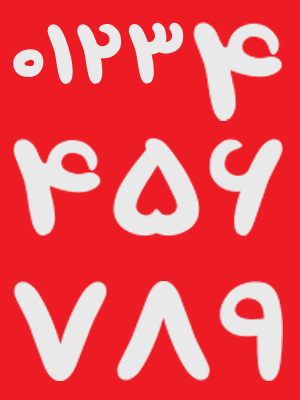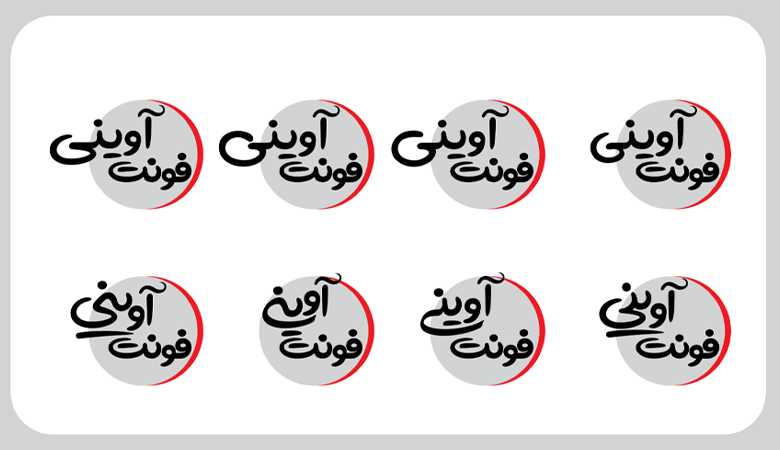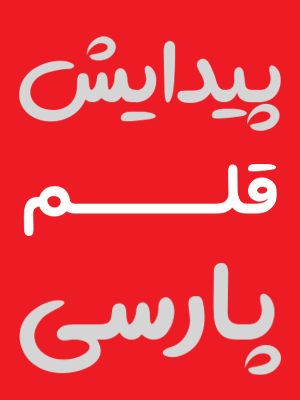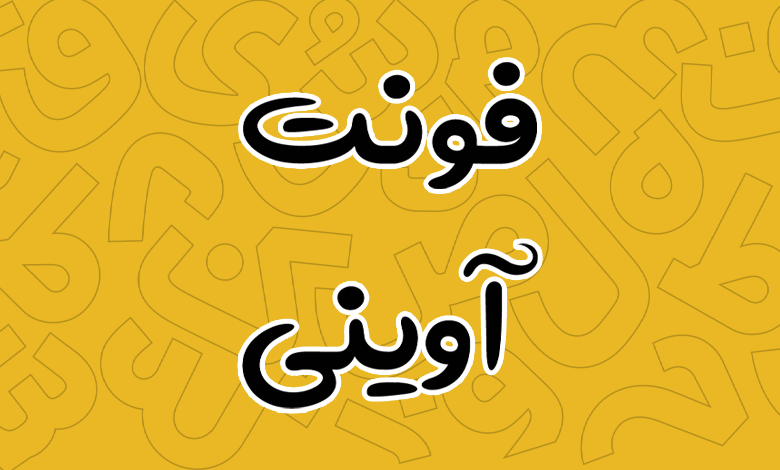
فونت آوینی (Aviny)
فونت آوینی (به انگلیسی: Aviny) فونت دستنویس فانتزی با ظاهری بسیار روان، پر تحرک و شاد است که در تمامی حروف از شکستگیها، دندانهها و قوسهایی بسیار نرم استفاده شده است. کاربردهای این قلم شامل فونت عناوین، نمایشی یا فونت مناسب تبلیغات و استفاده در متون کوتاه است. فونت آوینی رایگان نیست و در یک بسته با وزن معمولی رایگان جهت خرید ارائه شده است.
طراحی فونت آوینی بهدست قاسم نجاری صورت گرفته که دارای یک سبک خاص در ساخت فونتهای دست نویس و فانتزی است که پیش از این فونت جوان را از این طراح مورد بررسی قرار دادهایم. قلم آوینی نیز دارای یک حس جوان است که شادابی و نشاط را در متون شما ایجاد خواهد کرد.
در ادامه این نوشته از سایت فونتچی به نقد و بررسی کامل فونت آوینی خواهیم پرداخت که میتوانید با این فونتی که صرفا دارای یک وزن بوده اما امکانات و قابلیتهای متعددی در اختیارتان قرار خواهد داد آشنا شوید.
معرفی و بررسی فونت آوینی (Aviny)
فونت aviny در گروه فونت مناسب عنوان، دست نویس و مناسب تبلیغات گروهبندی شده است که برای استفاده در متون کوتاه، شعارهای تبلیغاتی و بهطور کلی هر جایی که نیاز به یک فونت دست نویس که ساختار کلی متون ما را تغییر داده و موجب جلب توجه شود کاربرد دارد.
سبک و وزن فونت آوینی
ساختار و شکل دست نویسی که این فونت میدهد میتواند برای ایجاد ارتباط صمیمیتر مورد استفاده قرار گیرد که توصیه میشود فقط در متنهای کوتاه از آن استفاده کنید.
از فونت اوینی میتوان در محیطهای مختلف دیجیتال و فضای آفلاین استفاده کرد. ساخت انواع عکس نوشته، طراحی بنرها و اسلایدرها برای سایتها و فروشگاهها، طراحی جلد کتاب در حوزه کودک و نوجوان، برنامههای تلویزیونی، ساخت کتابهای مصور و استفاده از این فونت در تیترها و عناوین هر چیز دیگری بیشترین کاربردهای این فونت هستند.
پشتیبانی از زبان عربی و انگلیسی
فونت آوینی فارسی جدایی از این زبان از زبانهای عربی و انگلیسی نیز پشتیبانی میکند. پشتیبانی از زبان عربی در این فونت مختص حروف و ترکیباتی که در زبان فارسی یکسان هستند نبوده و شامل اعراب و برخی کاراکترهای دیگر نیز میشود که همه گلیفها در هر دو زبان عربی و فارسی تا جای ممکن در حد استانداردهای بین المللی کار شده است.
شاید تنها ایرادی که بتوان در این خصوص به فونت آوینی گرفت، عدم اختصاص گلیفهای اعداد «۴۵۶» برای این زبان باشد که به شکل متفاوتی نسبت به زبان فارسی نوشته میشوند. انتظار هم میرود که با ارتقا این فونت به نسخه بالاتر این مورد برطرف گردد.
در خصوص زبان انگلیسی هم میتوان گفت که آوینی از فونت دیگری وام گرفته نشده و طراحی تمامی حروف لاتین بر اساس همان سبک دستنویس و فانتزی که برای زبان فارسی صورت گرفته، در زبان انگلیسی نیز پیاده سازی شده است.
دارای حروف و ترکیبات جایگزین
در بسته دانلود فونت آوینی که در کمتر فونت دستنویسی شاید بتوان آن را یافت، ترکیبات جایگزین یا همان حروف Alternative بسیار متعددی قرار داده شده است. آوینی دارای بیش از ۸۰۰ گلیف ترکیبی مختلف است که گاها روی حروف تکی و در موارد دیگر روی حروف دو و سهتایی که در ابتدا، انتها یا میانه کلمات مورد استفاده قرار میگیرند امکان تایپ نوشته را به شکل و ظاهر متفاوتی به شما خواهد داد.
به عنوان نمونه در همان تصویر بالا مشاهده میکنید که عبارت «فونت آوینی» در ۸ سبک خاص نوشته شده است که در این نمونه فقط ترکیب «ـی» با ظاهری متفاوت تایپ گردیده است. حال همین ترکیب در کنار سایر حروف مانند «ب، پ، ت، ث، س، ش» و دیگر ترکیبات ظاهر متفاوتی در اختیارتان قرار خواهد داد که شامل بیش از ۸۰۰ گلیف میشود.
سبک نقطه گذاری چسبان در حروف
در فونت آوینی با سبک فونت نقطه گرد مواجه هستیم و خبری از نقاط مربعی وجود ندارد. این فونت برای نقاط تکی به شکل کاملا گرد و ساختاری ساده است که در همه حروف یکسان هستند.
اما برای نقاط دوتایی و سه تایی نقاط از حالت گردی خارج شده و دارای ساختاری کشیده و خطی هستند تا ظاهر دست نویس فونت را حفظ کنند. نقاط دوتایی هرچه به سمت انتها پیش میروند کشیدهتر میشوند که این نوع نقطهگذاری بر اساس رسم خط با ماژیک است.
نقاط سه تایی نیز به همین ترتیب دارای ظاهری گرد و به هم چسبیده منحنی شکل هستند که در همه حروف بخش ابتدایی لاغرتر و هر چه به سمت انتها پیش میرویم انتهای نقاط کمی چاقتر شده و در پایان مقداری از چاقی آن کاسته میشود که در تصویر نمونه آن را میبینید.
مناسب عناوین، تبلیغات و کارهای گرافیکی
از مهمترین کاربردهای فونت آوینی میتوان برای استفاده در عناوین استفاده کرد که با توجه به وزنی که دارد و از سوی دیگر وجود ترکیبات جایگزین متعدد برای حروف فارسی که بیشترین استفاده را دارند، بدون نیاز به استفاده از نرمافزارهای گرافیکی سنگین همچون فتوشاپ و ایلستریتور، امکان تغییر شکل کلمات را به شکل زیبایی خواهد داد.
این فونت در تبلیغات اثرگذاری عالی روی مخاطب خواهد داشت که ظاهر دوستانه قلم دلیل بر آن است. از وسوی دیگر با توجه به سبک دستنویس خاصی که دارد، میتواند گزینه خوبی برای فونت عنوان جلد کتاب و مجلات باشد. خصوصا در حوزه داستان کودک و نوجوان که ارتباط دوستانه را ایجاد خواهد کرد.